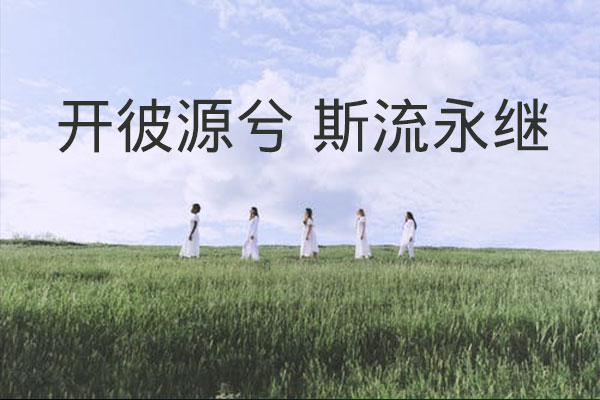
文泉驿微米黑
文泉驿微米黑是一个"自由字体"。该字体包含了所有常用简体中文、繁体中文所需要的汉字(最新版本包含超过20932个汉字,完整覆盖GB2312/Big5以及GBK标准字符集)。该字体同时还包含了日文、韩文和其他几十种语言符号。以外,该字体还包含了高质量的Droid Sans拉丁符号和Droid Sans Mono等宽字体,并内置Hinting和Kerning信息。微米黑字体文件极小,特别使用于便携式电脑设备。